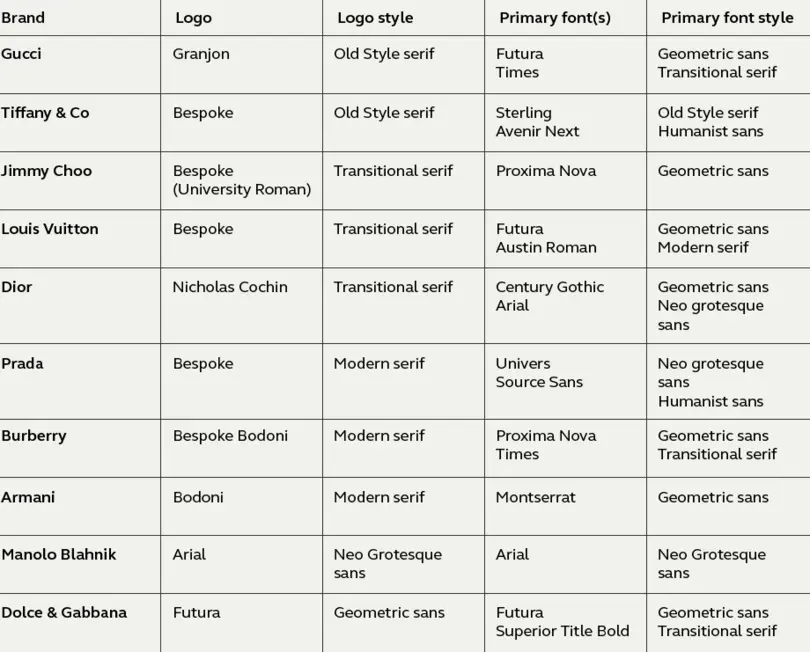
Polices et marques de luxe : la mode.
À la suite de notre analyse sur l’utilisation des polices dans les secteurs de la beauté et de l’automobile, nous nous intéressons ici à dix marques de mode de luxe. Quel est le style typographique le plus en vogue ? Comment ces marques utilisent-elles la typographie pour se différencier de la concurrence ? Y a-t-il des opportunités inexploitées ?
Gucci
De grandes images associées à une typographie géométrique créent une impression d’élégance, de modernité et de luxe. L’utilisation de Futura pour le texte s’accorde parfaitement avec Granjon dans le logo. Ces deux polices sont larges, ouvertes, accessibles et discrètes. L’utilisation de Times pour les descriptions de produits renforce l’impression de luxe, mais demeure un choix conventionnel et peu original, avec des traits fins qui peinent à être lisibles en petites tailles.
Tiffany & Co
Sterling (créée par Hoefler Type Foundry), une police avec empattement contrastée et délicate, est utilisée à la fois dans le logo et comme police principale. En raison de la finesse de ses traits, la typographie disparaît à petite taille, notamment dans le menu de navigation. Elle est utilisée en capitales pour les menus et légendes, et en bas de casse pour le texte courant, ce qui lui confère une allure élégante et luxueuse. Les polices humanistes sans-serif Avenir Next et Helvetica sont également utilisées dans certaines sections pour apporter une touche de modernité.
Jimmy Choo
L’alternance entre des lettres étroites et larges dans le logotype sur mesure University Roman JIMMY CHOO met en valeur la police principale Proxima Nova, créant ainsi une dynamique visuelle intéressante. L’association d’une photographie simple et d’une typographie propre, moderne et lisible donne une esthétique élégante, classique et sobre.
Louis Vuitton
Le monogramme personnalisé LV présente de gros empattements épais et des traits fins équilibrés, inspirés de la police Georgia, lui conférant force et robustesse. La typographie Futura est utilisée pour le mot-symbole Louis Vuitton et le texte, créant un bel équilibre visuel entre les deux polices. Sur leur site web, Georgia est également utilisée pour le texte, accompagnée d’Austin Roman et de LV Clemence, ce qui brouille légèrement la hiérarchie typographique.
Dior
Le logotype Dior incarne l’élégance, sublimée par des images en plein écran riches et dynamiques qui renforcent la sophistication de la marque. La police secondaire est Century Gothic, avec des légendes en majuscules et un texte en bas de casse. L’utilisation de Century Gothic Light donne au texte une apparence grise qui le rend plus discret. Le site web utilise également la police système Arial.
Prada
Le logo Prada repose sur une police serif moderne et sur mesure, audacieuse, iconique et distinctive. Le site présente de grandes images animées occupant tout l’espace, avec une typographie minimaliste. Le menu de navigation utilise Univers (en capitales), tandis que le texte principal est en Source Sans Pro, une police libre et open-source. La marque manque ici l’opportunité de refléter son style à travers sa typographie, qui semble avoir été choisie par défaut.
Burberry
Le logo de Burberry est une version élargie sur mesure de Bodoni, une police serif moderne qui évoque qualité et luxe. Proxima Nova est utilisée comme police principale pour les titres, légendes et corps de texte, en majuscules et bas de casse. Cependant, de nombreuses sections (navigation et texte) utilisent des caractères trop petits et difficiles à lire. L’usage de Times comme police secondaire apparaît comme un choix banal et peu pertinent.
Armani
La finesse du logo Armani Didot peut parfois nuire à sa lisibilité, mais cette police demeure une référence en matière de luxe, de style et de haute couture. Montserrat, une police sans-serif géométrique robuste et équilibrée, est également utilisée. L’esthétique repose sur des couleurs sombres et masculines, avec des images sérieuses. La marque affiche une identité moderne, classique et iconique, et sa typographie reflète ces valeurs.
Manolo Blahnik
Manolo Blahnik a adopté Arial comme police exclusive, l’intégrant uniformément dans toute son identité visuelle. Ce choix assure une certaine cohérence, mais Arial étant une police néo-grotesque présente sur tous les ordinateurs, elle peut manquer d’originalité pour une marque haut de gamme. L’avantage est que cette police a été optimisée pour l’écran, assurant une excellente lisibilité. Elle est présentée sur fond blanc avec beaucoup d’espace, ce qui renforce l’impression de sophistication. Les majuscules sont utilisées pour les titres et la navigation, accompagnées d’images très luxueuses, mais l’absence de différenciation typographique est une occasion manquée pour renforcer l’identité de la marque.
Dolce & Gabbana
Dolce & Gabbana est un assemblage éclectique de styles et de personnalités, associant diverses typographies sans véritable cohérence. On y retrouve une sans-serif géométrique, une serif transitionnelle, une sans humaniste, une écriture manuscrite au rendu crayeux, ainsi que Bodoni ! Le logo D&G utilise Futura Bold, une police géométrique aux proportions larges et arrondies. Toutefois, les versions plus légères utilisées dans la navigation et les légendes offrent une impression de grâce et d’élégance, mais le manque d’harmonie entre Futura et Avenir affaiblit la cohérence de l’identité visuelle.
Dans l’ensemble, on observe une tendance à privilégier le style au détriment de la fonctionnalité, ainsi qu’un manque surprenant d’imagination en matière de typographie. Il existe des problèmes fondamentaux de mise en page en termes de poids, de couleur et de taille. De nombreux agencements sont tout simplement illisibles à l’écran ( à l’image de Burberry, Tiffany, Dior et Gucci). L’utilisation de polices gratuites est fréquente, ce qui entre en contradiction avec l’image du luxe. L’identité de marque est essentielle, et bien que toutes ne voient pas l’intérêt d’une typographie sur mesure, l’usage d’Arial ou de Times ne permet aucune distinction entre haut de gamme et entrée de gamme, en particulier sur mobile, où l’espace pour les images est très restreint.